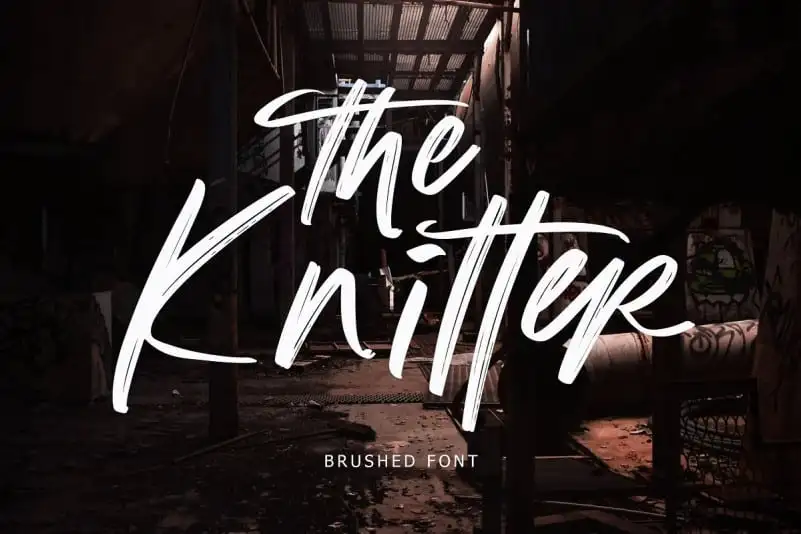
The Knitter Brush Font – Fonte Grátis
The Knitter Brush Font
A fonte The Knitter Brush Font é uma escolha ideal para aqueles que buscam um estilo casual e despojado no design tipográfico. Criada com a ajuda de um pincel seco, esta fonte display é perfeita para um uso criativo em diversos ambientes. Com origem na Lyth Creative, The Knitter Brush Font se assemelha à letra escrita a mão, mas oferece uma paleta de nuances e texturas únicas. Perfeito para estilos informais como logotipos ou mensagens digitais para eventos especiais como casamentos, esta fonte também é adequada para aplicativos mais formais como assinaturas, rótulos ou até mesmo camisetas. A sua flexibilidade de uso abrange uma variedade de aplicações, desde os headlines nas suas revistas e painéis de propaganda, aos materiais impressos em pequenas quantidades como os selinhos de convidado, notícias, panfletos, adesivos ou cartazes. A The Knitter Brush Font é certamente uma fonte que encoraja um toque criativo e pessoal em seu design visual.